<한글 디자이너 최정호>전시 : 명조체와 고딕체의 원형을 찾아서
명조체와 고딕체. 오늘날 흔히 통용되는 가장 널리 알려진 한글 글꼴일 것이다. 그 명성 뒤에 숨겨진 이름이 있다. 명조체와 고딕체의 원형을 만들었던, 출판계와 디자인계에서도 오랫동안 감춰져 있던 이름, 최정호. 한글 디자이너 최정호의 글꼴과 삶을 조명하는 전시가 한글날을 맞아 한 달 동안 파주출판도시에서 열린다.
한글 디자이너 최정호전
2015년 한글날을 맞이하여 안그라픽스와 파주 타이포그라피학교는 한글 디자이너 최정호의 글꼴과 삶을 조명하는 전시를 개최한다. 최정호는 평생을 원도 설계와 연구에 몰두한 1세대 글꼴 디자이너이자 연구자로 원도활자시대부터 사진식자시대에 이르기까지 수십 종의 한글 글꼴을 설계했다. 당대 뛰어난 완성도를 자랑했던 그의 원도는 오늘날 본문용 디지털 글꼴 ‘명조체, 고딕체’의 원형이 되었다. 하지만 그 큰 공로에 비해 그의 삶과 작업은 그다지 알려지지 않았다.
이 전시는 1950년대 민간 최초의 원도활자로서 수많은 문학 전집류와 백과사전류에 사용된 동아출판사, 삼화인쇄 활자체를 비롯하여 1970년대를 풍미했던 모리사와, 샤켄의 사진식자체는 물론, 말년기 미발표작인 초특태고딕체와 그의 마지막 원도 최정호체 등을 소개한다. 또한 ag 타이포그라피연구소에서 최정호 원도를 바탕으로 개발하고 있는 초특태고딕체와 최정호체 글꼴 개발과정과 이 글꼴을 활용한 그래픽 디자이너 10인의 포스터가 함께 공개된다.
이 전시를 통해 앞으로 출판계, 디자인계를 비롯하여 최정호의 글꼴을 읽고 쓰는 많은 사람들이 ‘한글 디자이너, 최정호’를 기억하고, 그의 작업이 오늘날 어떠한 의미를 지니는지 되짚어 보는 시간이 될 수 있기를 바란다.
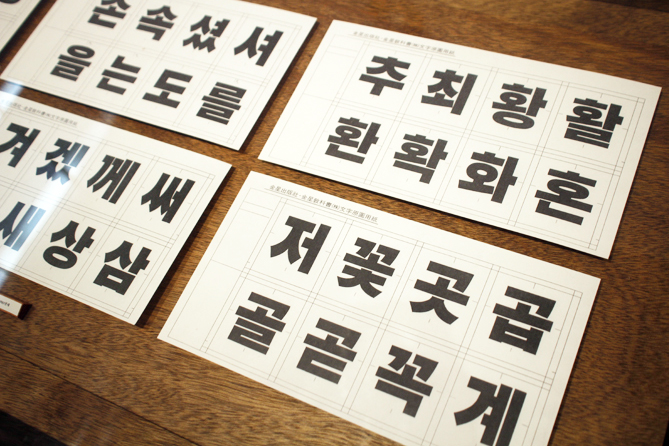
초특태고딕 원도 영인본 : 초특태고딕은 특태고딕보다 한 단계 더 굵은 민부리 계열 글꼴이다.
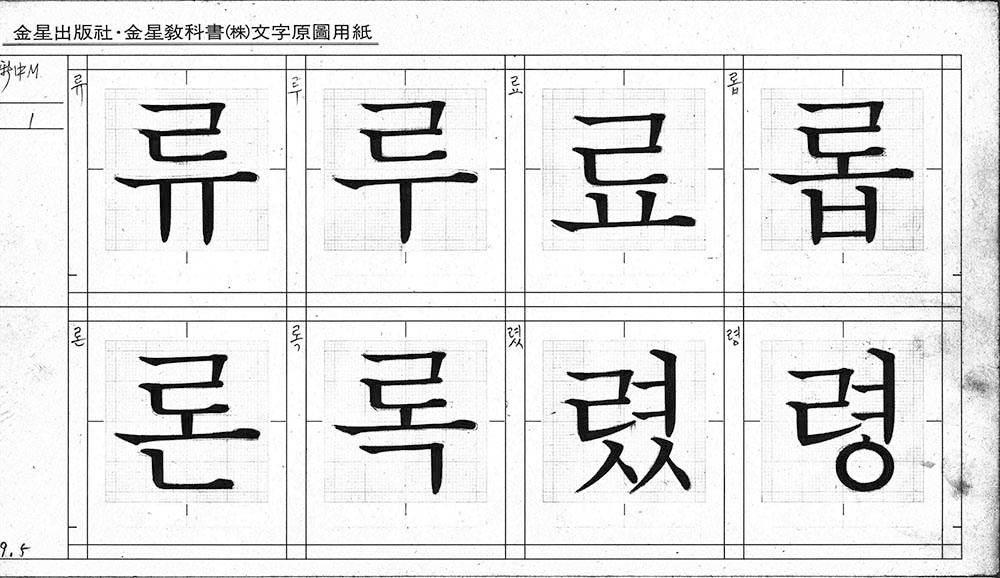
최정호체(위) / 초록태고딕체(아래) @한글 디자이너 최정호전 페이스북